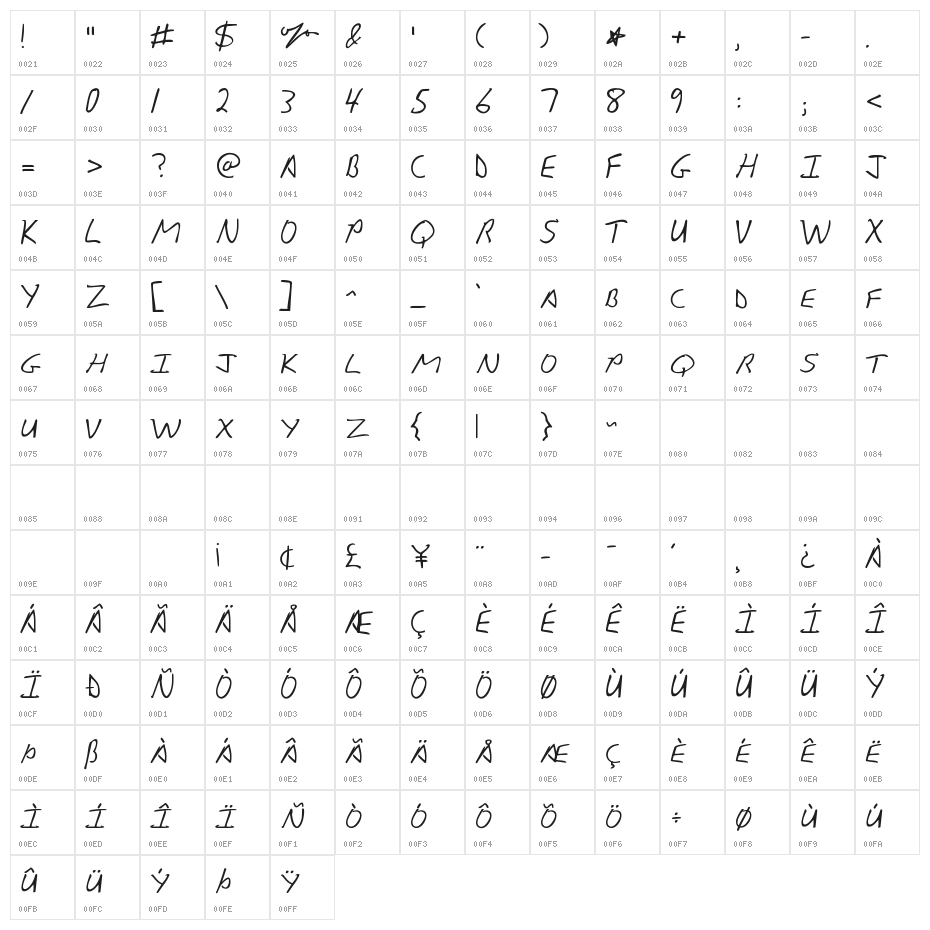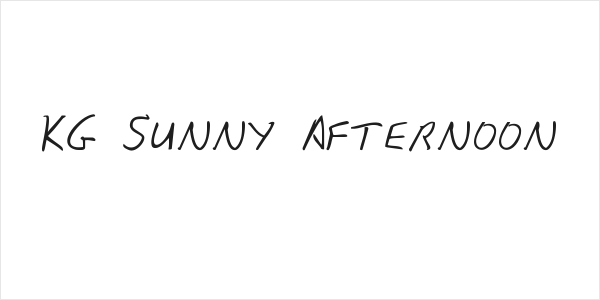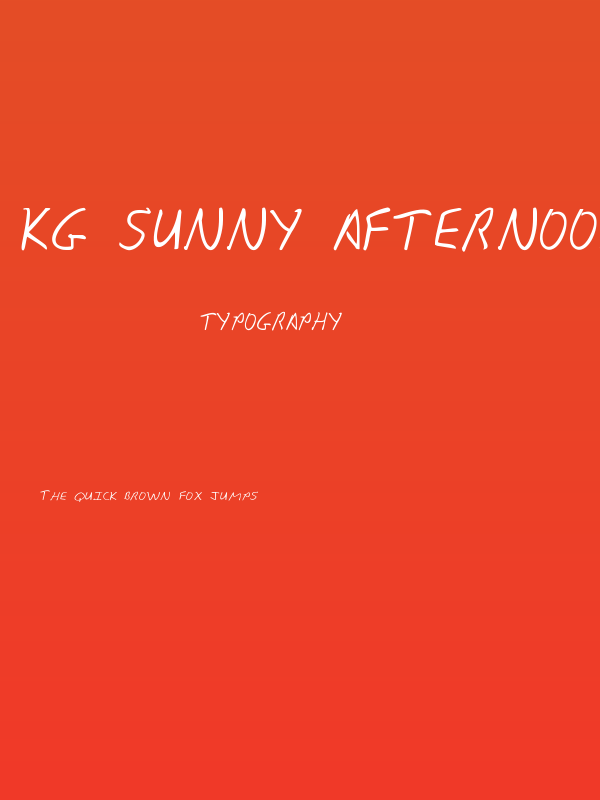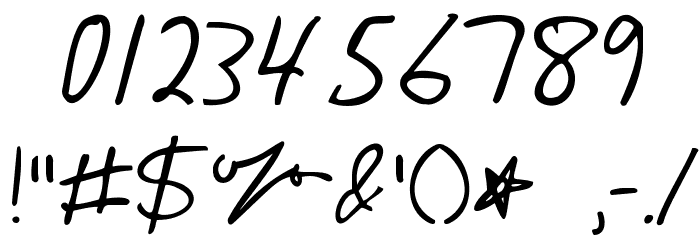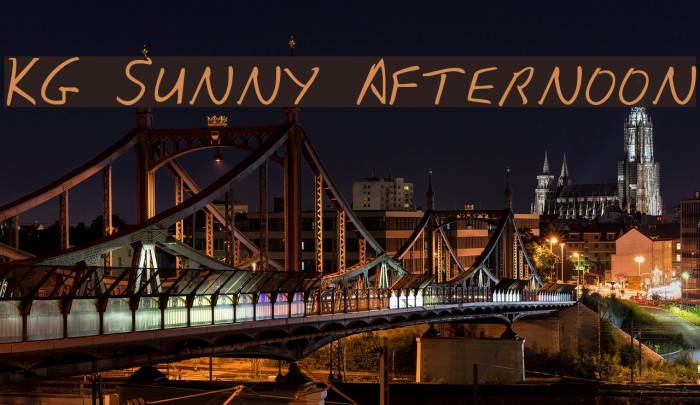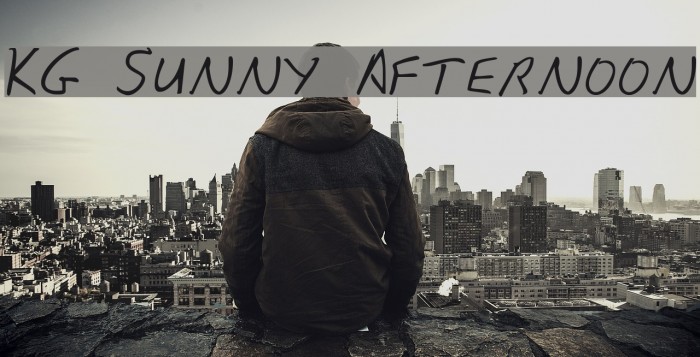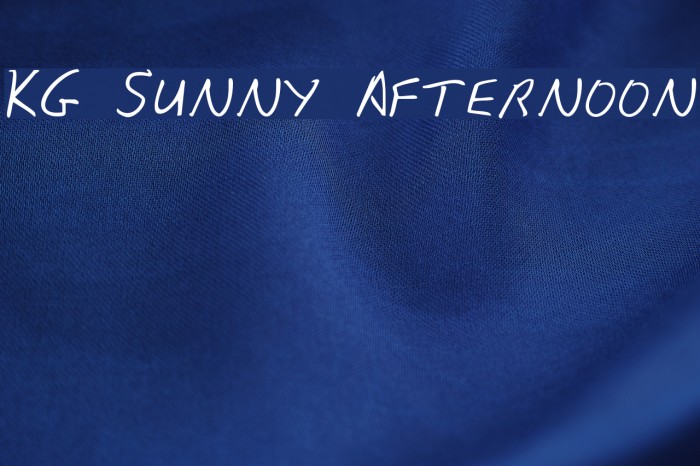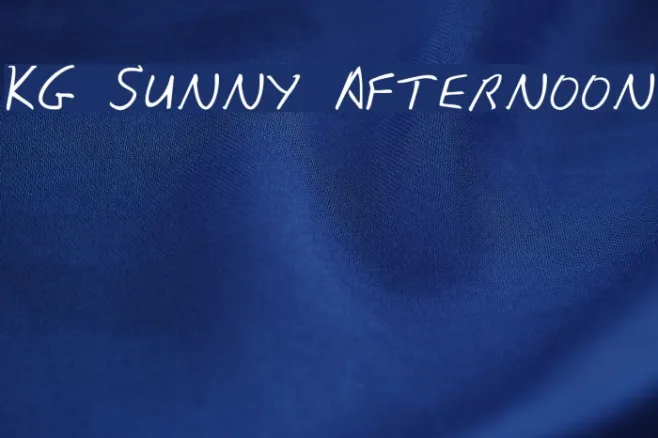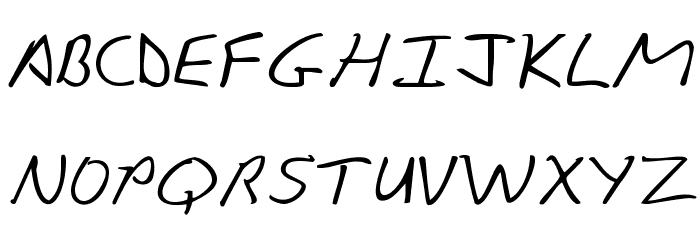
KG Sunny Afternoon Font
| Stile generale | Casual, Playful |
| Caso d'uso | Headlines, Informal Text, Personal Projects |
| Progetti proposti | Ideal for greeting cards, personal invitations, casual branding, and social media graphics. |